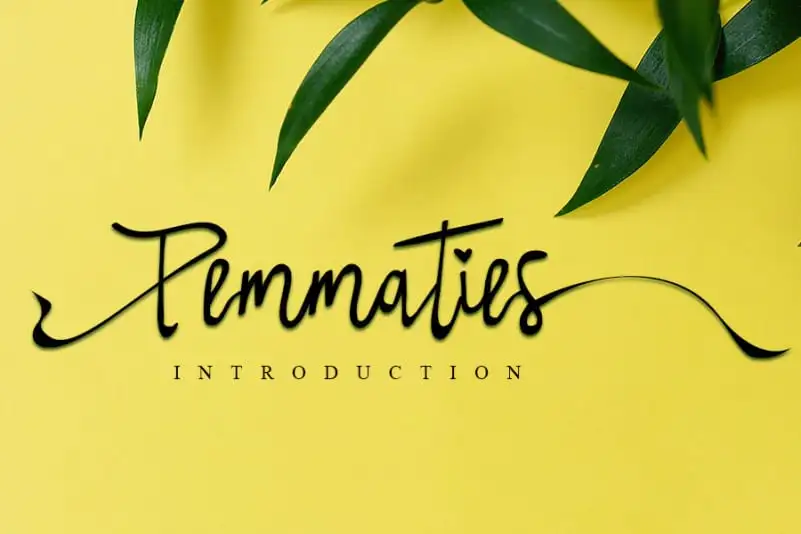
Temmaties Script Font – Download Grátis
A fonte ‘Temmaties Script Font’ é uma escolha ideal para quem busca uma solução elegante e contemporânea. Ela mantém seus contínuos elementos tipográficos, enquanto oferece um toque inovador que a torna perfeita para diferentes projetos de design. Suas linhas fluidas e suas influências da caligrafia garantem uma aparência sofisticada e refinada que se adapta facilmente aos mais variados usos. Seja para criar cartões de visita, estilos ou até mesmo papelaria, a ‘Temmaties Script Font’ oferece um grau de flexibilidade que será extremamente benéfica tanto para designers quanto para aquelas pessoas que desejam personalizar suas mensagens de maneira única e criativa. A fonte é perfeita tanto para o design gráfico profissional quanto para as necessidades pessoais, tornando-a uma escolha muito versátil para aqueles buscando uma solução elegante e moderna.